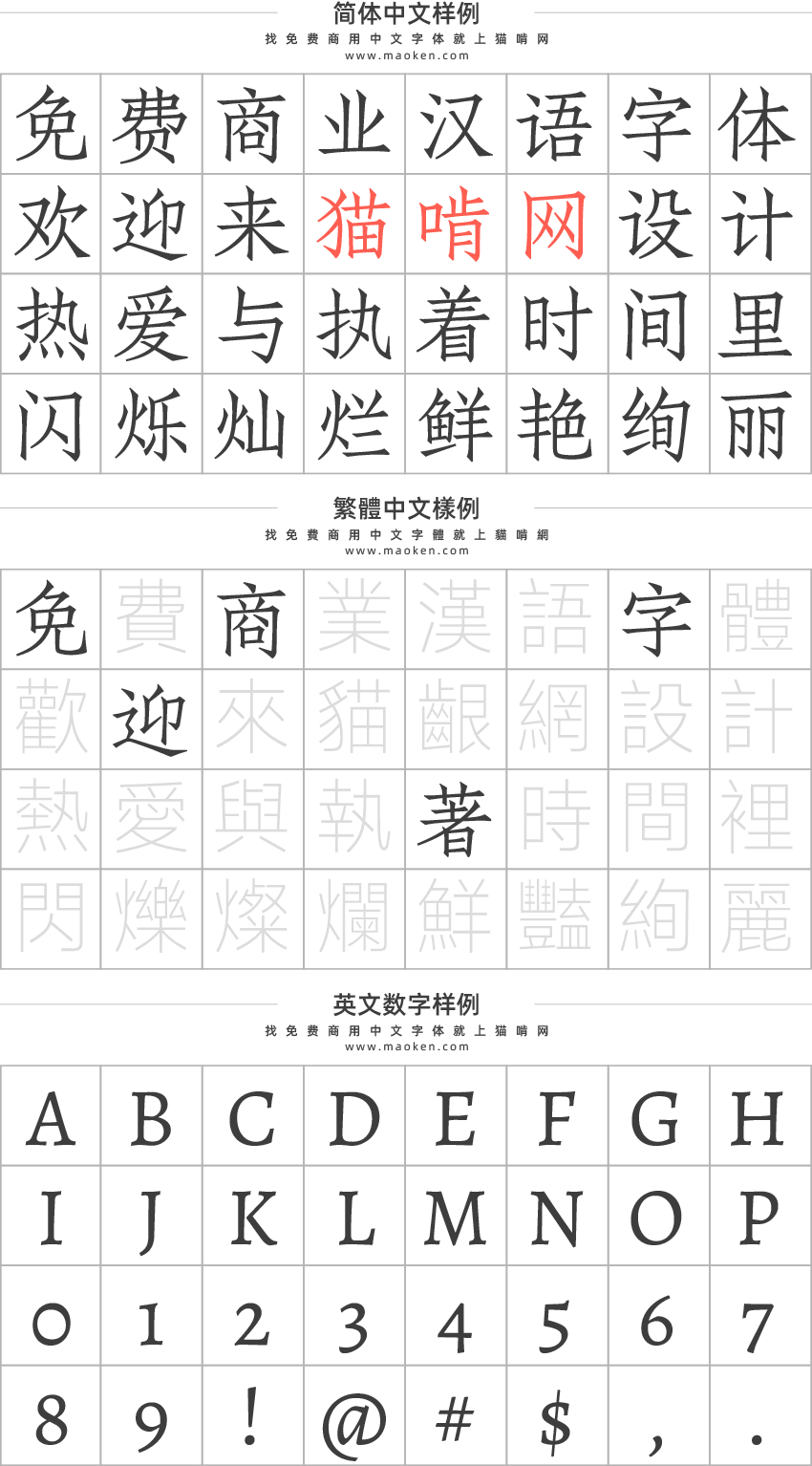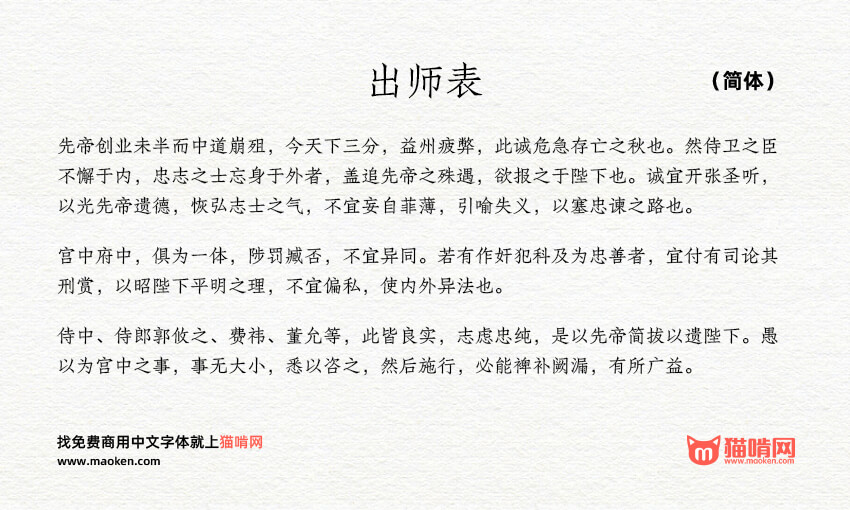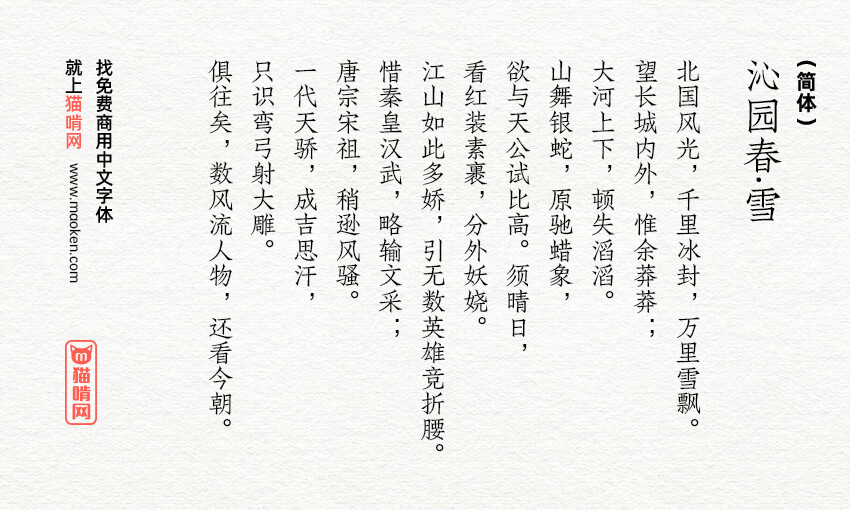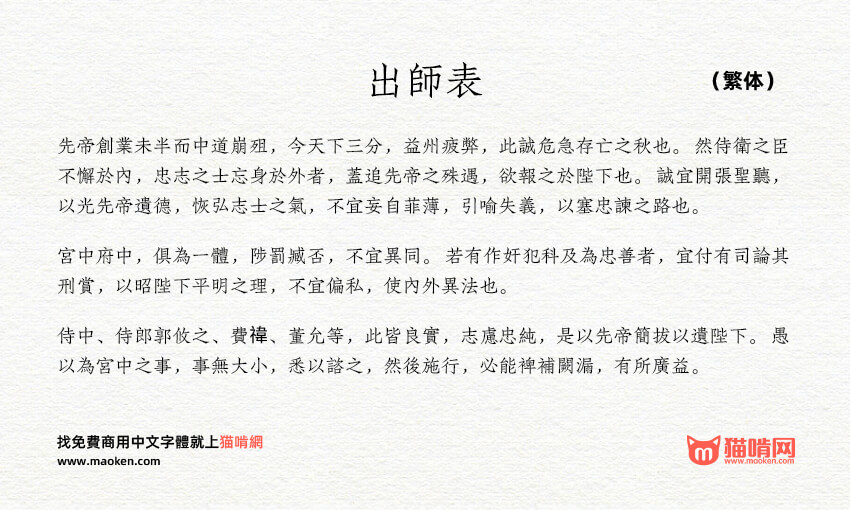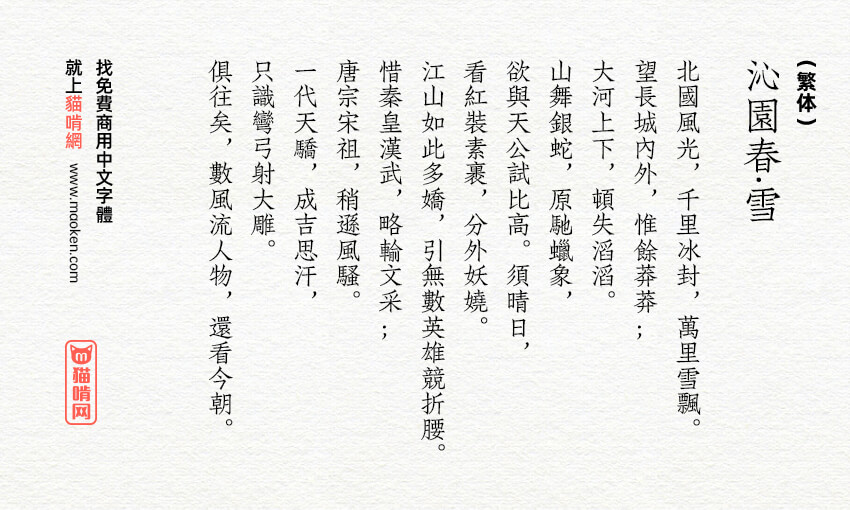
朱雀仿宋:融入朱雀文化元素的免费商用仿宋字体
朱雀仿宋」是璇玑造字的开源仿宋字体计划,志在最终提供高质量的、支持多语言的正文仿宋解决方案。
仿宋作为「宋黑仿楷」中文四大基础字体之一,长期缺乏开源许可证下的选择。我们希望「朱雀仿宋」可以弥补这一空缺,为开源软件与 TeX 社区贡献一份力。
上世纪初,仿宋活字一度品类繁盛,开发、应用风行一时。然而时过境迁,市面上的仿宋最终收敛于「华丰真宋」一系,这也是今天大多数人所熟悉的仿宋样貌。「朱雀仿宋」则以民国仿宋活字「南宋」为蓝本,在满足现代排印需求的前提下,尝试为正文仿宋字库带来一缕新鲜空气。
当前我们发布的「朱雀仿宋」仍为「预览测试版」,尚处于项目早期阶段;无论是设计风格还是字形、排版质量,都不代表正式版情况。因此,
「朱雀」的未来,由你定义
璇玑正在尝试一种全新中文字库设计模式。得益于我们开发的最新技术,璇玑的设计师可以直接将人工智能作为设计工具去使用,我们也因此能以迭代的方式开发「朱雀」。
设计故事
智琮的智能造字技术可以让设计师将 AI 作为设计工具去使用,可快速从拼字甚至是手写字优化成高质量的风格字形。
开发一套开源仿宋字库的想法最早始于 2021 年初,是继「未来荧黑」项目之后,我们认为更有意义、也更具难度的挑战。随着设计研究的深入与技术进步,特别是去年以来 AIGC 技术的爆发,实现这一想法在今日遂成可能。
《足本欧阳永叔全集》,1936 年大东书局刊行。使用南宋活字排印,主创自藏。
「朱雀仿宋」改刻自民国活字「南宋」,试图为这套沉睡数十年的字体赋予新生。「南宋」是 1932 年「百宋书局」推出的仿宋体活字,韩佑之设计原稿,邹根培雕刻字模。一经面世,即广泛用于书籍、期刊排印。「南宋」与大多数正文字体的设定不同的是,它中宫收紧,重心略靠右下,撇捺舒展,笔画的粗细变化强烈,含蓄秀美而充满力量感,在排印标题和正文时展现出浓厚的「书卷气」。
在「南宋」活字的基础上,「朱雀仿宋」稍稍削弱了笔画的对比度,适当地规整了字形结构与版面效果,同时最大程度地保留了「南宋」的独特气质与活字趣味。
「朱雀」是中国传统文化中「四象」之一,南方七宿之神。以「朱雀」为名,暗合了「南宋」渊源与「璇玑造字」的品牌名。
• 落霞孤鹜的「霞鹜文楷」、Fontworks Klee One、思源宋体,这些开源字体是本项目人与机在设计过程中的写法参考。
势力、力量 字体有点问题。看上去总感觉斜着的,我感觉是 力 字的问题。大家伙觉得呢?
少数屏幕和印刷品都很合适的仿宋,希望能出个TC版本(既原版民国南宋的字形)
朱雀仿宋:这款字体的 走之 旁,是地地道道的 折弯 样式。比起其他几款由宋体拉长的 类似仿宋的替代字体(走之旁 就是直接一竖),更贴近中国风格。好字!非常看好、非常期待这款字体能更广而告之地,被大家和业界喜爱和广泛使用。团队用心了!